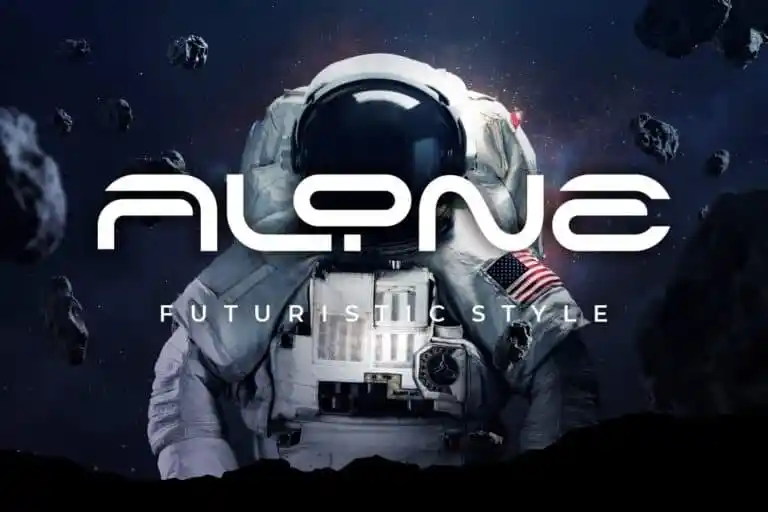
Alone Display Font
A ‘Alone Display Font’ é uma nova criação da HansCo, inspirada na forma elegante de uma logomarca específica. Desenvolvida para uso em pequenos espaços, a fonte se destaca particularmente no design de logotipos e cenas rápidas do título, brilhando com eficácia quando invertida sobre um fundo branco – muito como ocorreu na criação da própria marca que inspirou seu conceito. Com traços afiados e modular, esta fonte é perfeita para quem busca uma tipografia moderna e marcante. Ideal tanto para aplicativos digitais quanto para materiais impressos em pequenas amostras ou gráficos de alta visualidade, a ‘Alone Display Font’ oferece um toque único e chamativo que certamente tornará qualquer projeto mais especial.